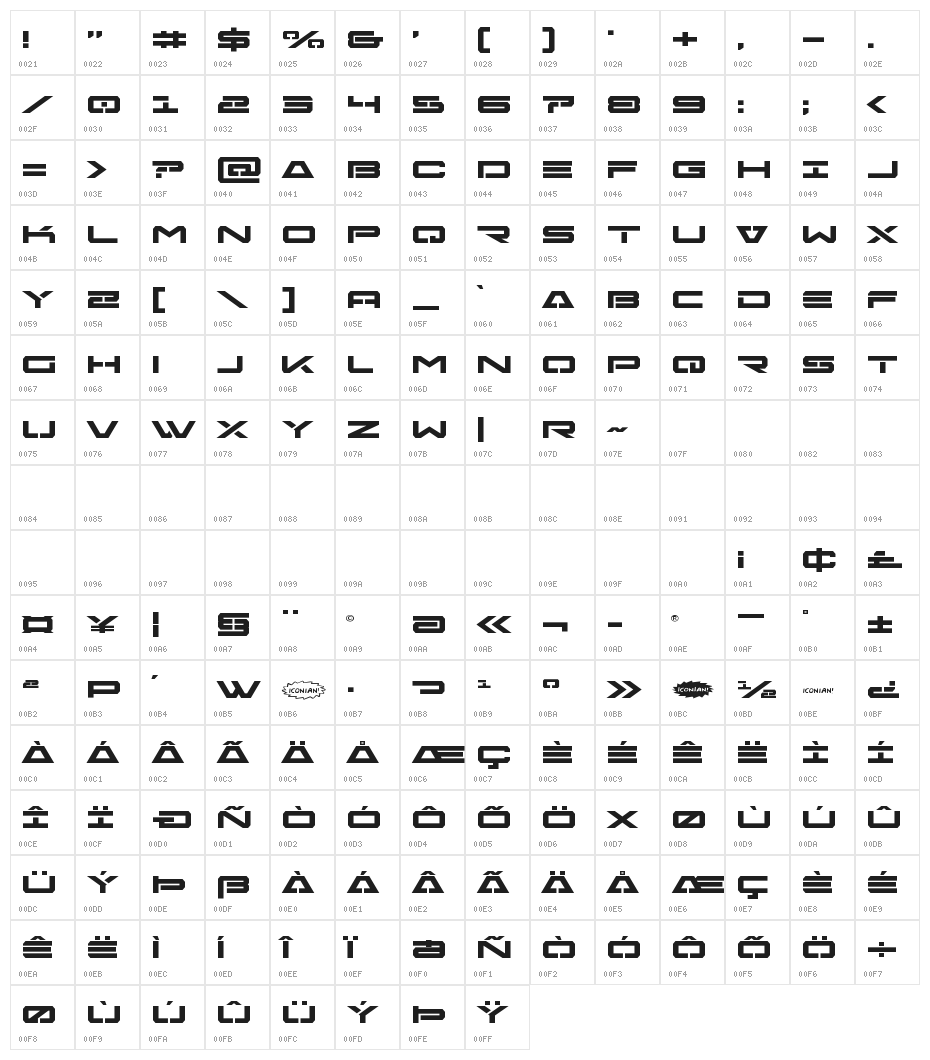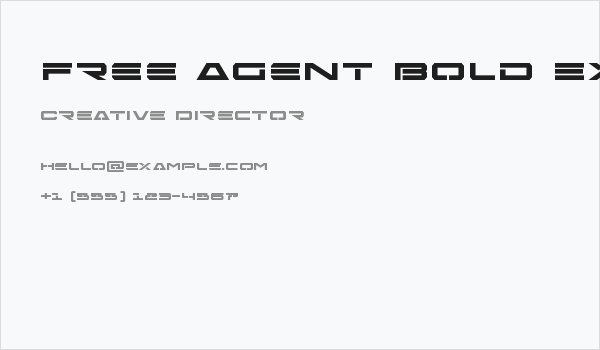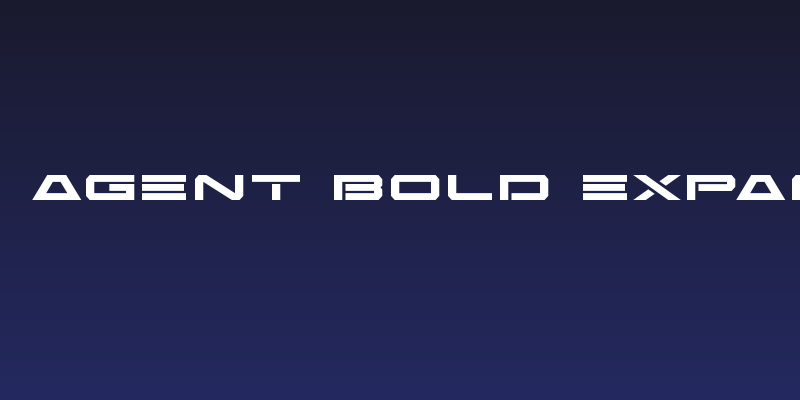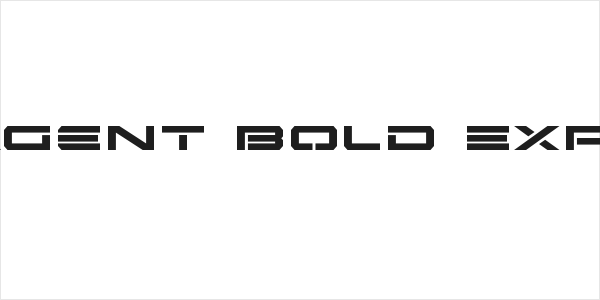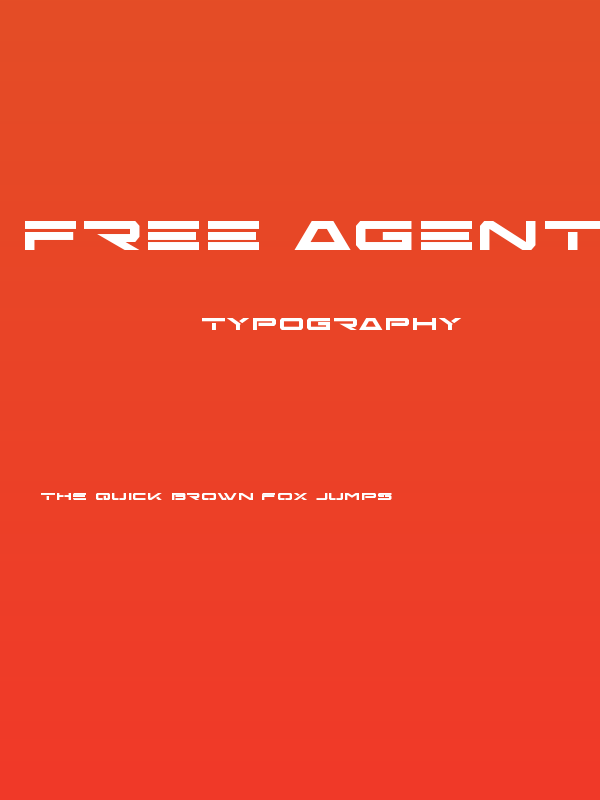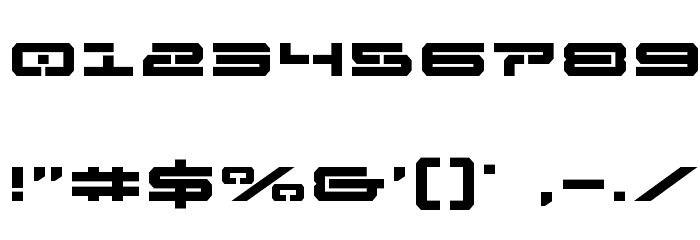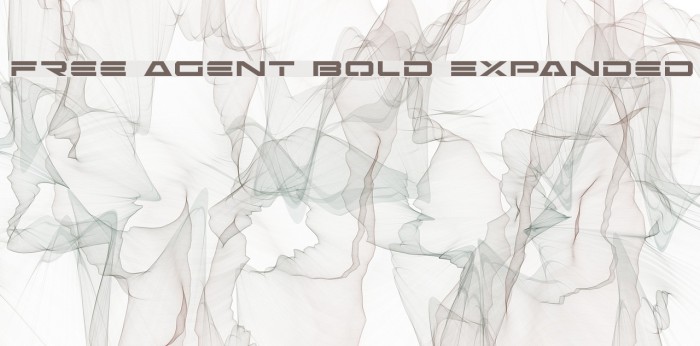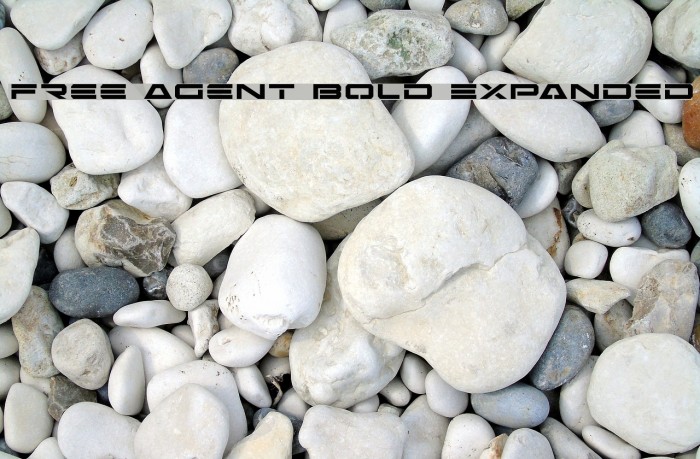
Free Agent Bold Expanded Font
| Vorgeschlagene Projekte | Ideal for technology branding, sci-fi posters, video game titles, and futuristic-themed designs. |